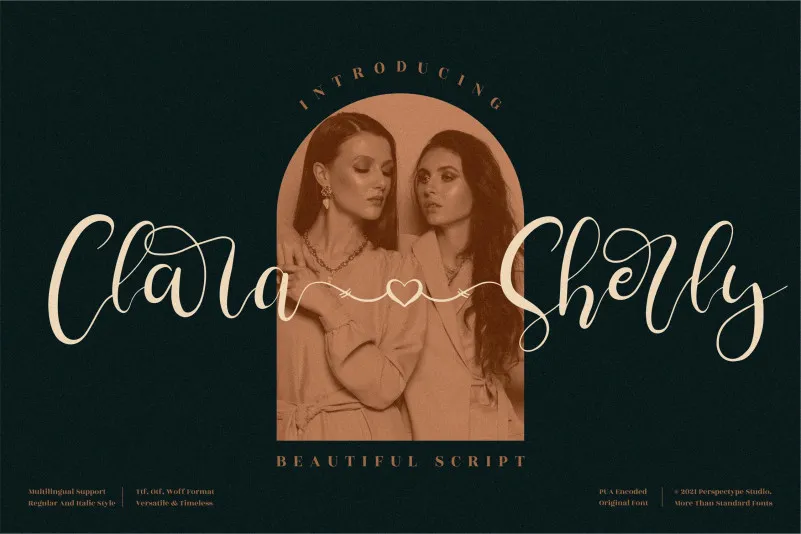
Clara Sherly Font – Fonte Grátis
Clara Sherly Font
A fonte Clara Sherly é uma elegante e refinada escolha para designers profissionais buscando estilo moderno e sofisticado. Com seu visual arrojado e moderno, essa font se destaca especialmente como opção perfeita para criações de logomarca, identidade corporativa, convites, material de endereço, design de casamento e até postagens nas redes sociais. Clara Sherly é uma font script que traz a essência moderna do mundo digital ao seu trabalho, sem sacrificar o luxo e classe tradicional. Seja para um projeto personalizado ou para uma campanha de marketing, ela oferece facilidade na criação de design com PUA (Private Use Area) encodado, permitindo que você acesse todos os caracteres e “swashes” de forma simples e eficaz. Clara Sherly é ideal tanto para quem quer dar um toque sofisticado em seu trabalho quanto para aqueles que estão sempre buscando novas maneiras de inovar. Sua capacidade única de oferecer acesso a todo o conjunto de caracteres torna-a uma fonte versátil e adaptável, perfeitamente adequada para um vasto leque de aplicativos design.